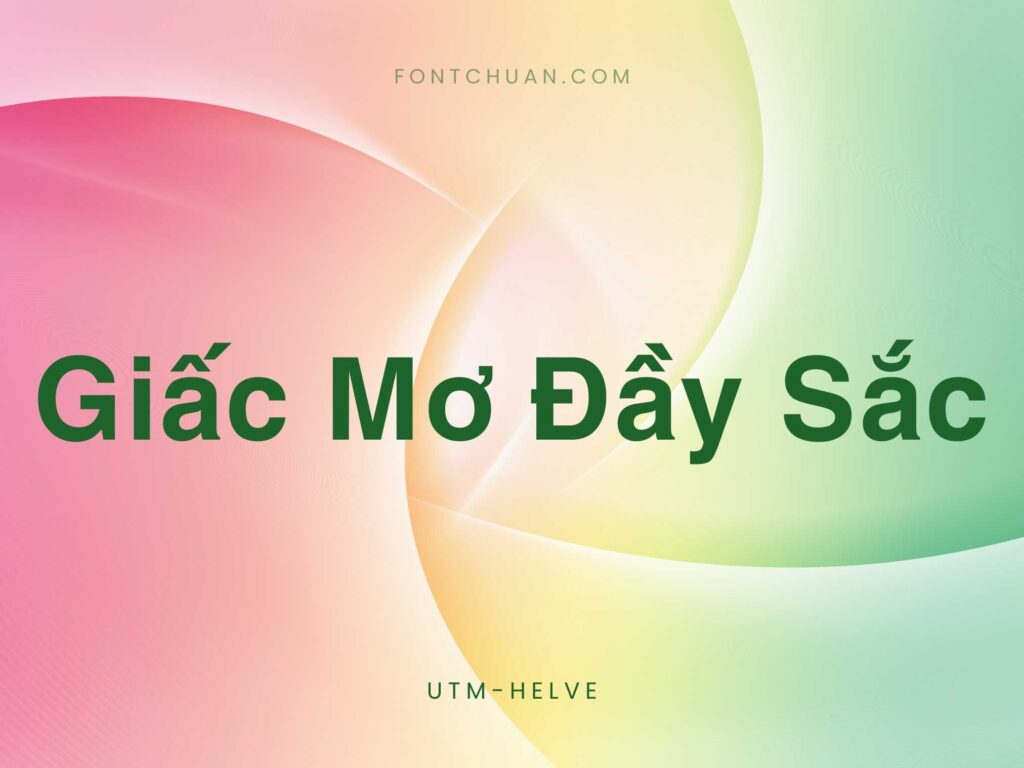
UTM Helve là một font chữ sans-serif hiện đại, lấy cảm hứng từ font Helvetica nổi tiếng, mang đến sự tối giản và chuyên nghiệp trong thiết kế. Font này có hình thức gọn gàng, rõ ràng và phù hợp cho nhiều mục đích sử dụng khác nhau. Font đã được Việt hóa bởi Thiên Minh, hỗ trợ đầy đủ tiếng Việt cùng hơn 200 ngôn ngữ khác, giúp mở rộng khả năng ứng dụng trong nhiều lĩnh vực thiết kế. Thành viên của Font Chuẩn đã sưu tầm và giới thiệu font này nhằm đáp ứng nhu cầu bạn đọc, cung cấp nguồn tham khảo chất lượng và ứng dụng thực tế vào các dự án thiết kế
Về đặc điểm thiết kế, UTM Helve có các đường nét sạch sẽ, độ dày đồng đều, giúp cải thiện khả năng đọc ở mọi kích thước. Font này phù hợp với nhiều ứng dụng như thiết kế thương hiệu, tài liệu chuyên nghiệp, website, trình bày văn bản, bảng hiệu và biển quảng cáo. Đặc biệt, với sự rõ ràng và dễ đọc, UTM Helve còn là một Font chữ giáo dục lý tưởng, thích hợp cho sách giáo khoa, tài liệu học tập, bài giảng và các ấn phẩm đào tạo, giúp nâng cao hiệu quả truyền đạt thông tin và trải nghiệm học tập.